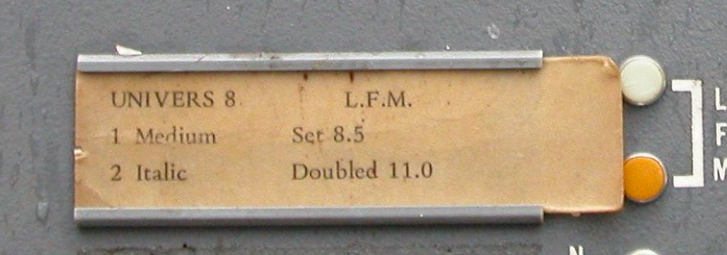
Liste von Compugraphic Schriften, Frühe '70er
Vor kurzem hatte ich mal ein kleines Projekt, bei dem ich mich absichtlich etwas beschränken wollte auf ein Layout, inkl. Schriftwahl, das auch so Anfang der 70er nicht zu exotisch oder Handarbeit gewesen wäre, als Referenz dachte ich da an den Photosatz der Zeit. Also was man mit einem "CompuWriter I/II" hätte machen können.
Dafür ist das jetzt nicht mehr so relevant - ich nahm einfach Times -  aber die Frage blieb trotzdem noch offen was möglich gewesen wäre. Klar findet man Listen von Compugraphics Schriften, aber selten mit Zeitangaben, und da die ja gerade später tiefer im Geschäft waren sagt das wenig über diese Zeit aus.
Ein paar "Artefakte" die man online fand:
Von einem Bild eines Compuwriters. Univers passt ja zur Zeit.
Aus einem Kolophon. Zu "English 49" findet man fast nichts im Internet, aber Times ist natürlich nicht überraschend, da die Compuwriter ja auf kleinere Zeitungen abziehlten.
Noch ein Kolophon. Wieder English 49, dazu Helvetica, wobei "Jetsetter" als Anbieter hier auch keine sehr ergebnisreiche Suche ergab.
Ich hatte auch noch ein niedrig aufgelöstes Bild wo ich "Helios" dachte zu lesen, was ja m.W. die CG Helvetica Variante direkt war.
In Adrian Frutiger's "Schriften - Das Gesamtwerk" gabs auch noch ein paar Referenzen auf CG als Lizensat (z.B. bei Glypha oder Serifa), aber das scheint eher später zu sein (1976+).
Wie gesagt, ich habe jetzt keinen direkten Nutzen mehr daran, aber aus reinem historischem Interesse würde es mich schon interessieren was damals den Nutzern des doch vergleichsweise preiswerten Systems zur Verfügung stand.
ich kann mich leider auf Anhieb nur noch als Ergänzung an die VAG Rounded erinnern. Wir hatten aber mit Sicherheit ca. 20 verschiedene Schriften auf zwei großen Floppy Disc gespeichert.
nach intensivem Nachdenken bin ich noch auf folgende Schriften gekommen: Antique Olive, Triumvirate, Helios, Univers, VAG Rounded.
Moin, zu Compugraphic Anfang der 70er kann ich nichts beitragen, doch –falls auch interessant– zum letzten Drittel. „A portfolio of display typefaces“, Fourth Edition, May 1979, ca. 108 Seiten, 215x277 mm. Anbei das IHV und ein Bericht über das Schriftportfolio.